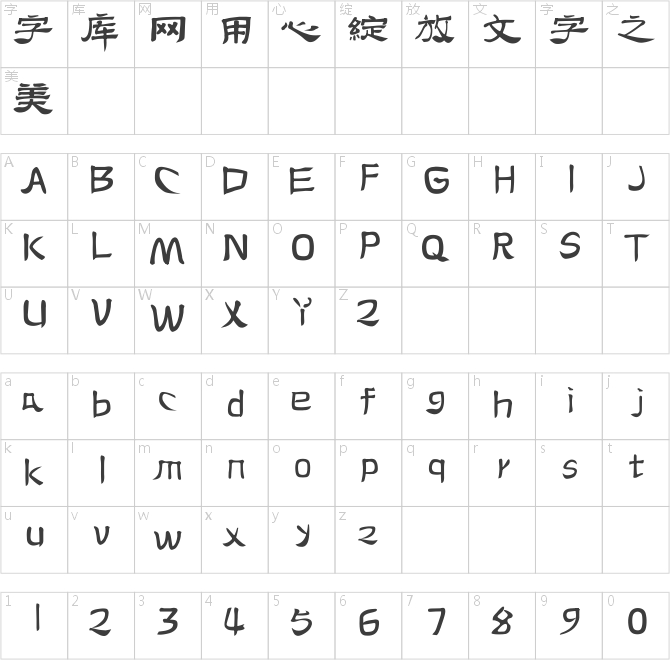
字体名称: 逐浪海昏侯汉简
逐浪海昏侯汉简隶书
2011年,江西南昌出土了惊世的汉代海氏侯古墓群,这是我国有史以来最重要的考古挖掘成果之一。
2005,南昌郊区的海昏侯汉代墓考古发现正式向外布宣传,震惊业界。
随着江西南昌汉代海昏侯墓考古发掘出了一批竹简 这批竹简被寄予厚望,被认为是整座海昏侯墓出土的最重要文物之一 其中就包含失传1800年的《论语》知道篇。
为了更好的恢复这一文化,逐浪软件团队根据披露的竹简文字,进行复古与再制,实现现代字库的制程,使用数字技术,真实呈现西汉文字。
字体创作原则:
1、  完全遵从出土字简构字。
2、  复古,而不泥古,针对现代汉字横排进行优化,同时保留竖排的形式感。
3、  基于现代字库进行优化。
基于GB2312标准,同时加入逐浪生僻字专用库,为传统与现代,架接桥梁。